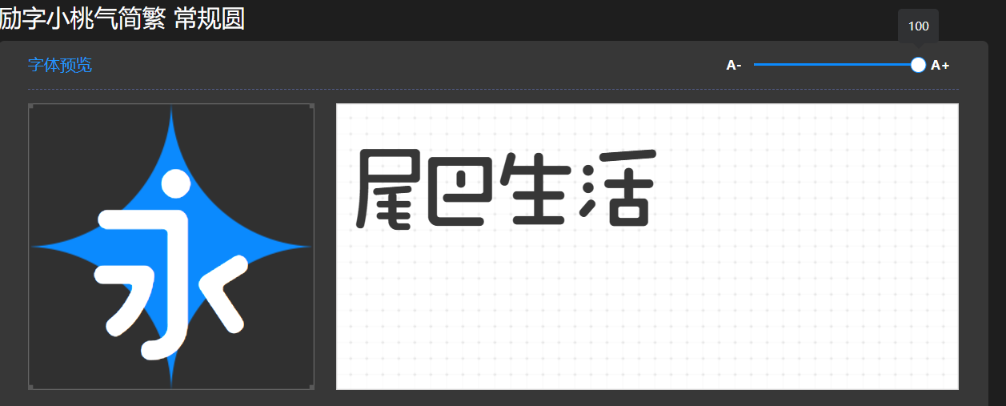
萌宠包装新物种——励字小桃气简繁,一款可爱俏皮的手写字
“我爱我的猫,与外貌、性别、纯种还是流浪, 全都不相干
一百万只猫,就有一百万种可爱
爱只有不同, 没有高下
伴随萌宠经济的兴起以及Z时代对陪伴的需求,萌宠作为Z时代青年的必需品,萌宠经济也被推上了浪潮。
每只萌宠宝贝都是独特的存在,无论其性别、外貌或品种,它们都值得被无条件地爱和关怀。针对品牌对不同萌宠的定义及营销需求,励字造梦字库推出一款俏皮可爱的手写字——励字小桃气简繁,完美契合萌宠的心灵定位以及包装所需。
励字小桃气简繁,一款以手写感为基础的圆体,字型上松下紧,重心略低,结构松弛灵活,变化多样。 整体笔形圆润饱满,舒展流畅。统一的笔画设计,折笔处内外圆角兼备,用圆形元素代替部分笔画,丰富了视觉效果。 笔画之间根据空间和位置采用了“断开”的处理方式,增加了轻快的整体风格,具有良好的视觉表现与阅读体验。